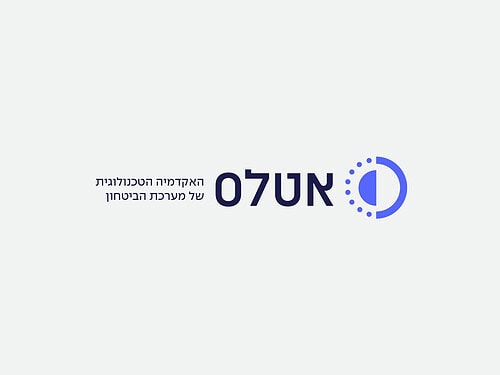
על אודות פונט אינדקס
בעוד הוא מציג סגנון טכנולוגי המושפע מעולם התיכנות וההייטק, פונט אינדקס שומר על קשר אותנטי לגופנים גיאומטריים מרוח הבאוהאוס כדוגמת ״ספיר״ ו״תחיה״, ובד־בבד מרפרר לאותיות Typewriter ישנות.
אינדקס הוא פונט דו־לשוני אקסצנטרי הממזג בין עבר ועתיד בדרך ייחודית. הוא מגיע בחמישה משקלים, ועובד נהדר בכותרות, לוגואים, שילוט וקטעי טקסט קצרים.
בנוסף, קיימת לפונט גרסה נפרדת של אותיות ברוחב אחיד בשם ״אינדקס מונו״.
הפונט כולל נִקּוּד מְדֻקְדָּק, מספר OpenType Features™ חיוניים ותמיכה מלאה בעברית, אנגלית ועוד 218 שפות לטיניות (באותיות Uppercase). -
OpenType Features
- ליגטורות סודיות אש ← אש
- www ← www
- חלופות סגנוניות ?! ← ?!
- 0 ← 0
- אותיות רחבות ﬡﬢﬣﬤﬥﬦﬧﬨ